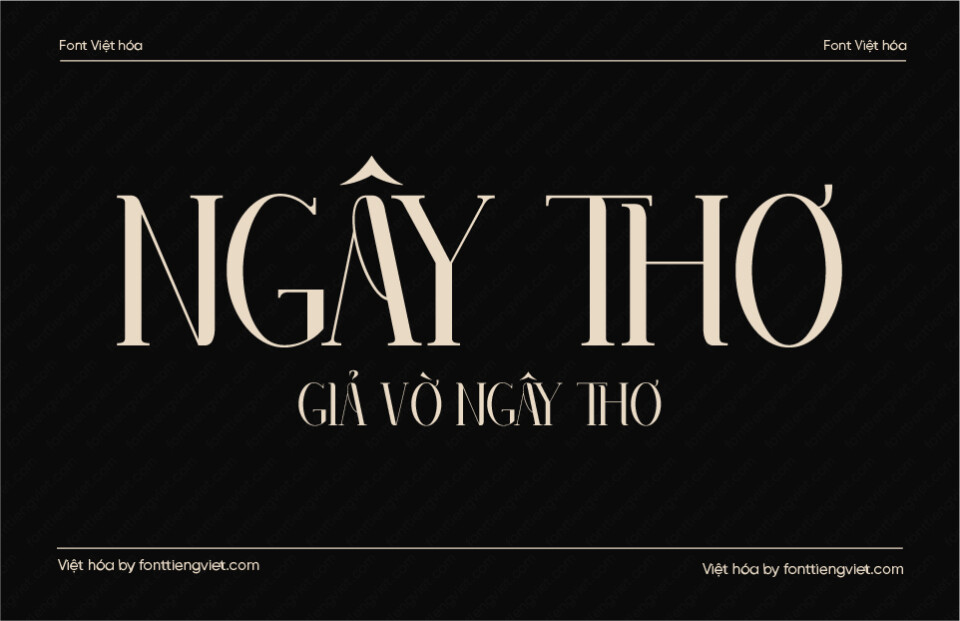
Font Việt hóa 1FTV VIP Ameng
Giới thiệu về Font Việt hóa 1FTV VIP Ameng trong học tập
Trong môi trường giáo dục hiện nay việc lựa chọn một bộ Font Miễn Phí phù hợp đóng vai trò vô cùng quan trọng để giúp học sinh tiếp thu kiến thức một cách tốt nhất. Font Việt hóa 1FTV VIP Ameng xuất hiện như một giải pháp hoàn hảo cho các thầy cô giáo và các em học sinh khi cần một phông chữ có đường nét rõ ràng nhưng không kém phần sáng tạo. Đây là bộ phông chữ được tối ưu hóa riêng cho bảng mã tiếng Việt đảm bảo không xảy ra lỗi hiển thị khi soạn thảo văn bản hay làm bài thuyết trình slide. Với kiểu dáng hiện đại và thanh lịch Font Việt hóa 1FTV VIP Ameng giúp cho các nội dung giảng dạy trở nên sinh động và thu hút sự chú ý của các bạn nhỏ trong mỗi tiết học thú vị trên lớp.
Những ưu điểm vượt trội của Font Việt hóa 1FTV VIP Ameng
Khả năng hiển thị sắc nét trên mọi thiết bị
Một trong những điểm cộng lớn nhất của Font Việt hóa 1FTV VIP Ameng chính là độ tương thích cao. Dù bạn đang sử dụng máy tính chạy hệ điều hành Windows hay macOS thì bộ phông chữ này vẫn giữ được độ sắc nét tuyệt đối. Điều này đặc biệt có lợi cho nhà trường khi triển khai các giáo án điện tử trên màn hình tivi hoặc máy chiếu. Đường nét của Font Việt hóa 1FTV VIP Ameng được thiết kế với độ dày vừa phải giúp người xem không bị mỏi mắt khi quan sát trong thời gian dài. Ngoài ra các ký tự dấu thanh tiếng Việt như huyền sắc hỏi ngã nặng được đặt ở vị trí rất chuẩn xác tạo nên sự cân đối tổng thể cho toàn bộ đoạn văn bản giúp học sinh dễ dàng làm quen với mặt chữ chuẩn mực.
Văn phong thiết kế phù hợp với lứa tuổi học đường
Font Việt hóa 1FTV VIP Ameng mang phong cách trẻ trung năng động nhưng vẫn giữ được sự chỉn chu cần thiết của một sản phẩm giáo dục. Các bạn học sinh có thể sử dụng bộ phông chữ này để trang trí báo tường làm thiệp tặng thầy cô hoặc trình bày các báo cáo ngoại khóa sinh động. Sự linh hoạt trong cách thể hiện giúp Font Việt hóa 1FTV VIP Ameng trở thành lựa chọn hàng đầu cho các câu lạc bộ nghệ thuật và các phòng truyền thống tại trường học. Việc ứng dụng các phông chữ việt hóa chất lượng cao còn góp phần bồi dưỡng thẩm mỹ cho thế hệ trẻ ngay từ khi còn ngồi trên ghế nhà trường.
Kết luận về bộ Font Việt hóa 1FTV VIP Ameng cho trường học